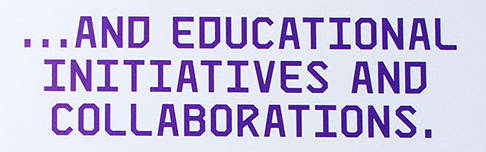
Guggenheim Helsinki
ich bin auf der Suche der dieser Schrift.
WhatTheFont hat leider keine brauchbaren Ergebnisse geliefert.
Bin hier darüber gestolpert.
Instead of using Futura, we were able to choose Architype Renner, which includes some nice alternate characters Futura doesn’t have. We used Architype Renner for the frame of the layout, while the titles and the main content utilise the more experimental and architectural Skyhook Mono.